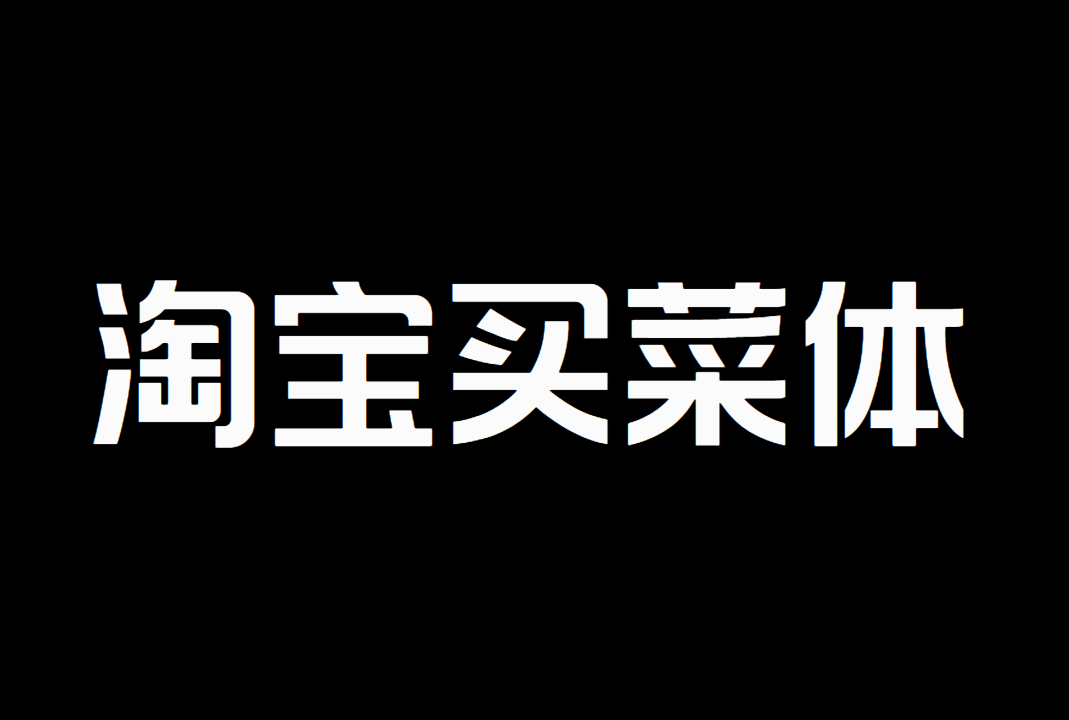
淘宝买菜体(TaoBaoMaiCaiTi)是由淘宝买菜携手通义锦书,倾力打造了一款独具匠心的AI个性化免费商用中文字体,通过智能AI技术,赋予字体独特的质感和生命力。
淘宝买菜体(TaoBaoMaiCaiTi)智能AI字体不仅拥有丰富的中文字符库,覆盖GB2312标准,包含超过6974个汉字,可覆盖大部分使用场景。